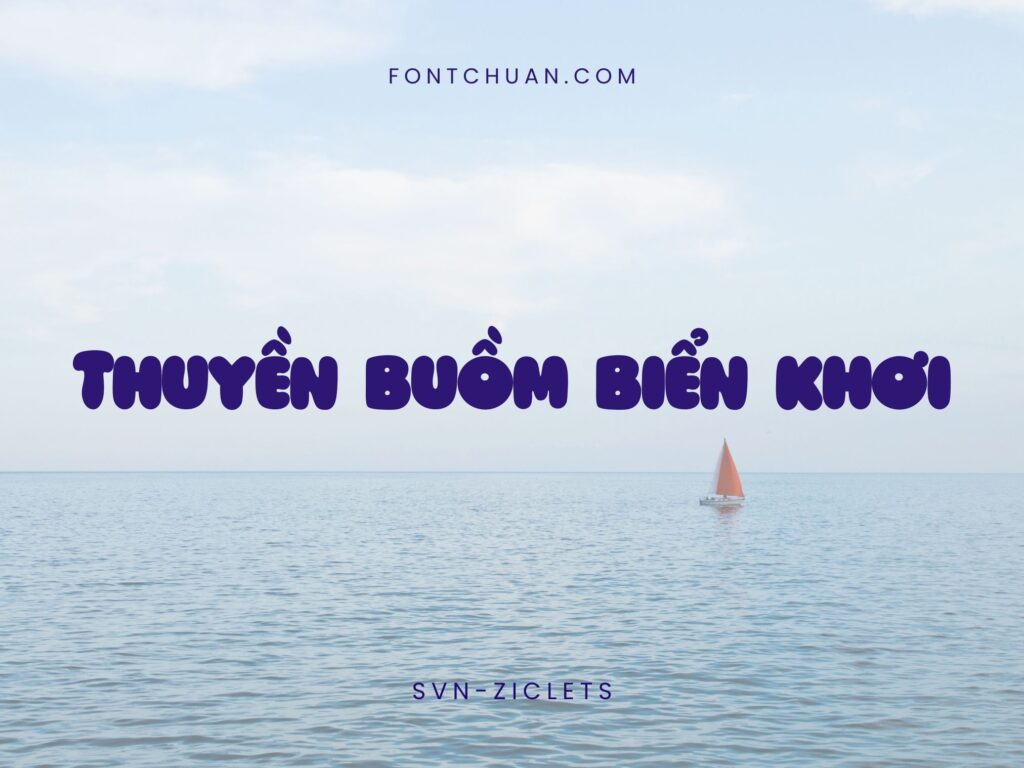
Font SVN Ziclets Việt Hóa
Font SVN Ziclets là phiên bản Việt hóa của kiểu chữ Ziclets, được thực hiện bởi Styleno.1 Fonts. Ziclets là một Font Decorative mang phong cách truyện tranh và trẻ em, được thiết kế bởi Ricardo Marcin & Erica Jung và phát hành bởi PintassilgoPrints. Font này nổi bật với các đường nét mềm mại, vui nhộn và độc đáo, tạo cảm giác thân thiện và hấp dẫn. Ziclets bao gồm các chữ cái in hoa, in thường, chữ số và các ký tự đặc biệt, phù hợp cho nhiều mục đích thiết kế khác nhau.
SVN Ziclets lý tưởng cho các dự án thiết kế yêu cầu sự vui tươi và sáng tạo, như thiết kế logo, tiêu đề, bao bì sản phẩm và các ấn phẩm quảng cáo. Các ngành nghề như giáo dục, ẩm thực và spa có thể tận dụng font này để tạo điểm nhấn trong thiết kế. Ngoài ra, font cũng thích hợp cho các sự kiện như Tết, Giáng sinh, Sinh nhật và các lễ hội khác.